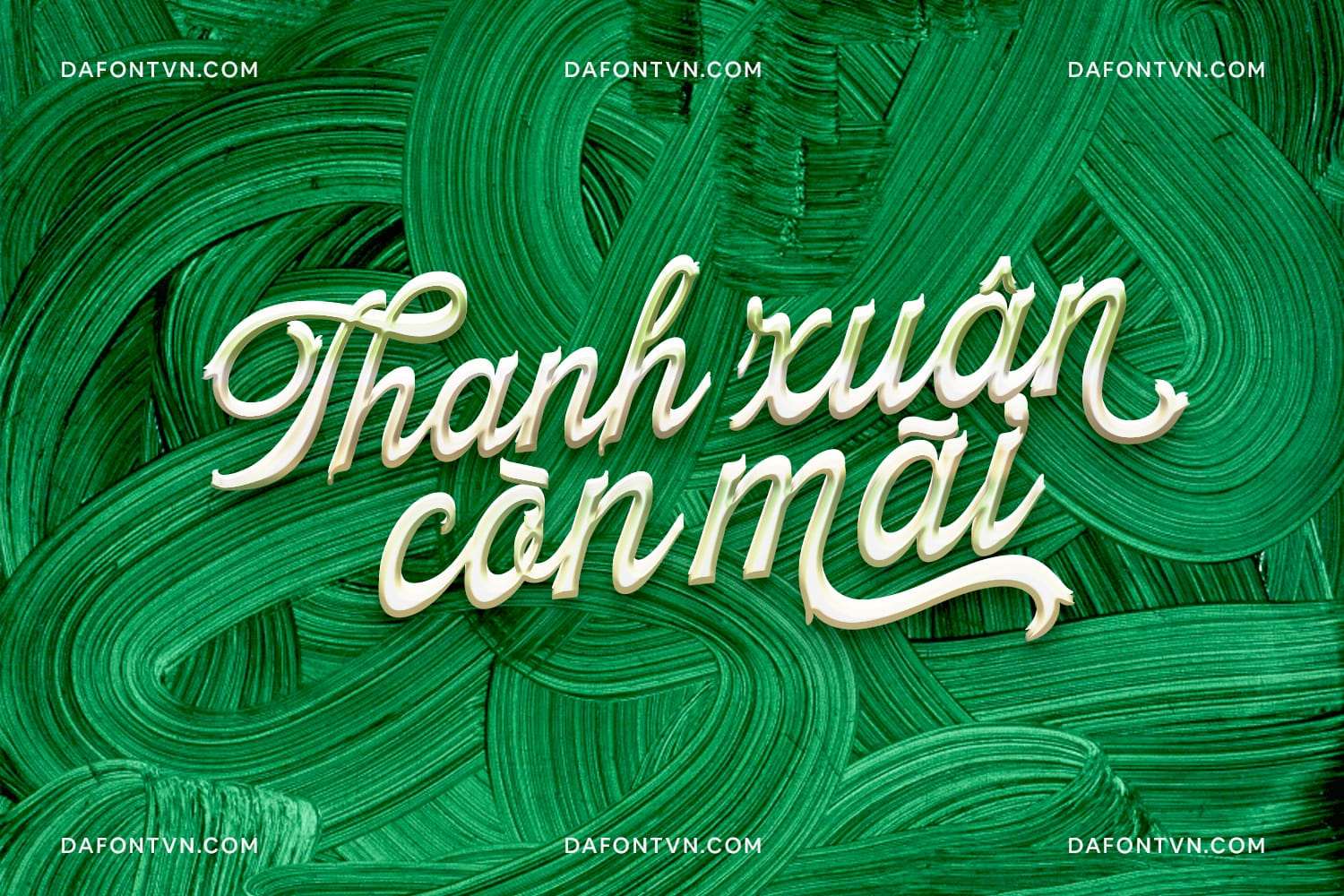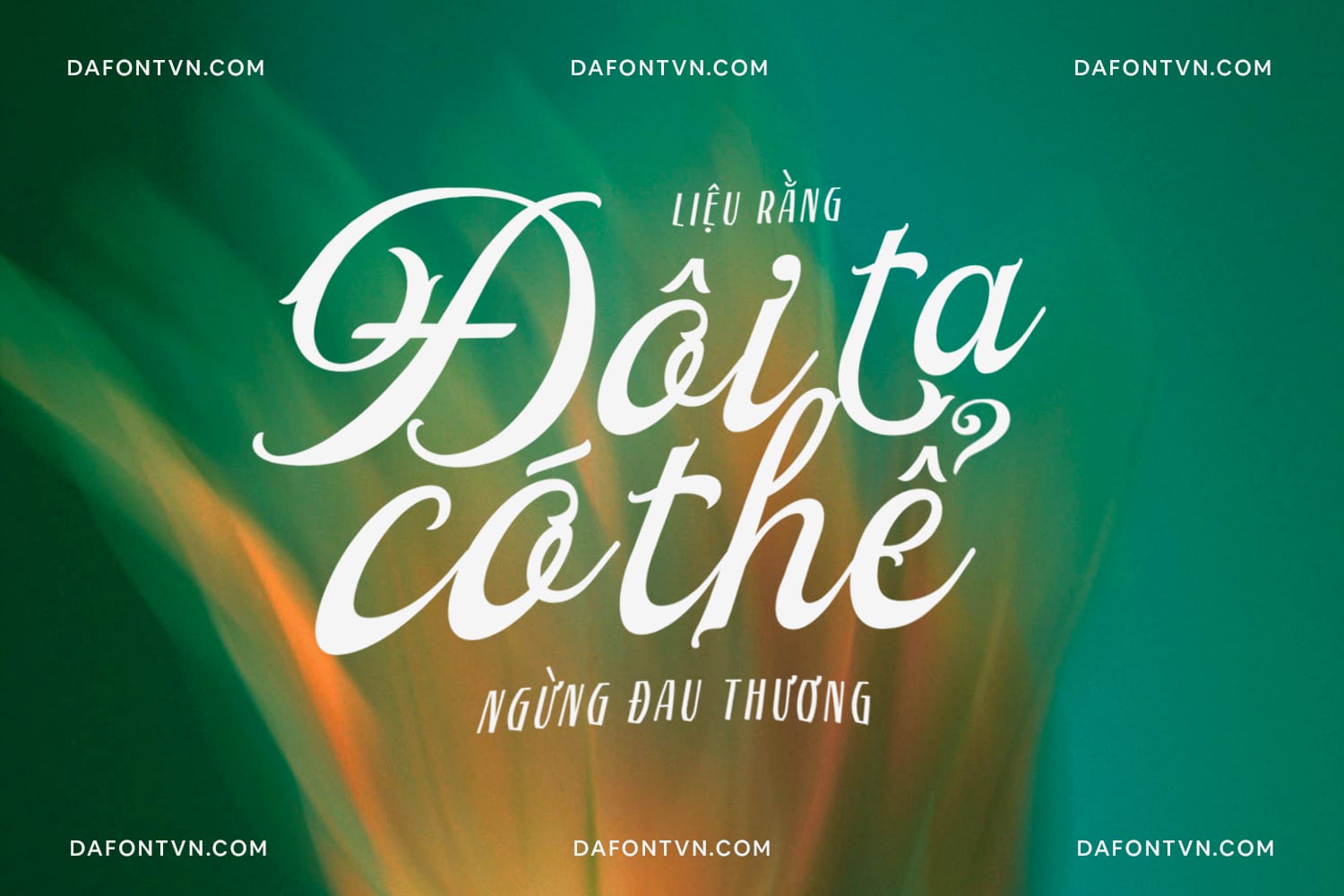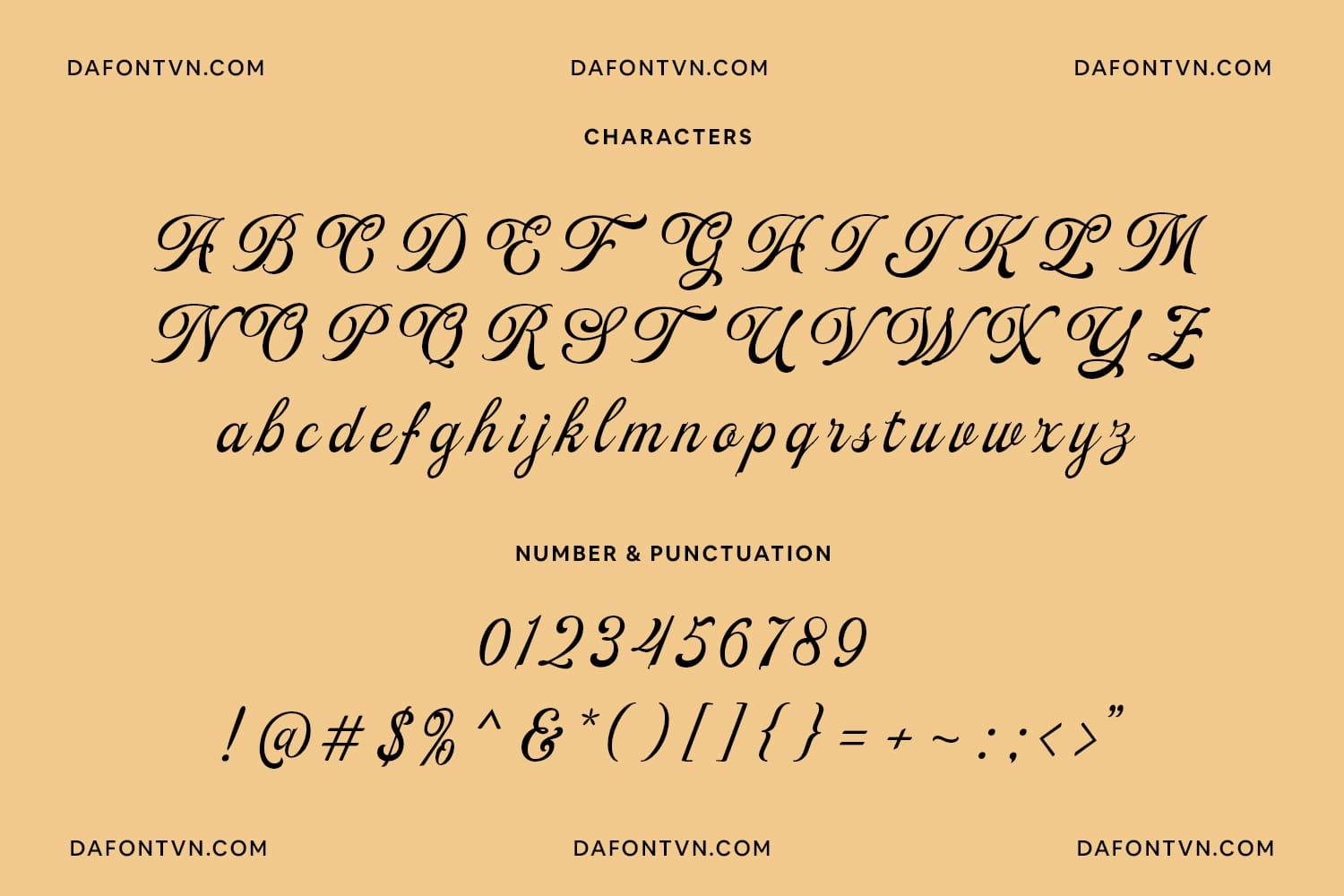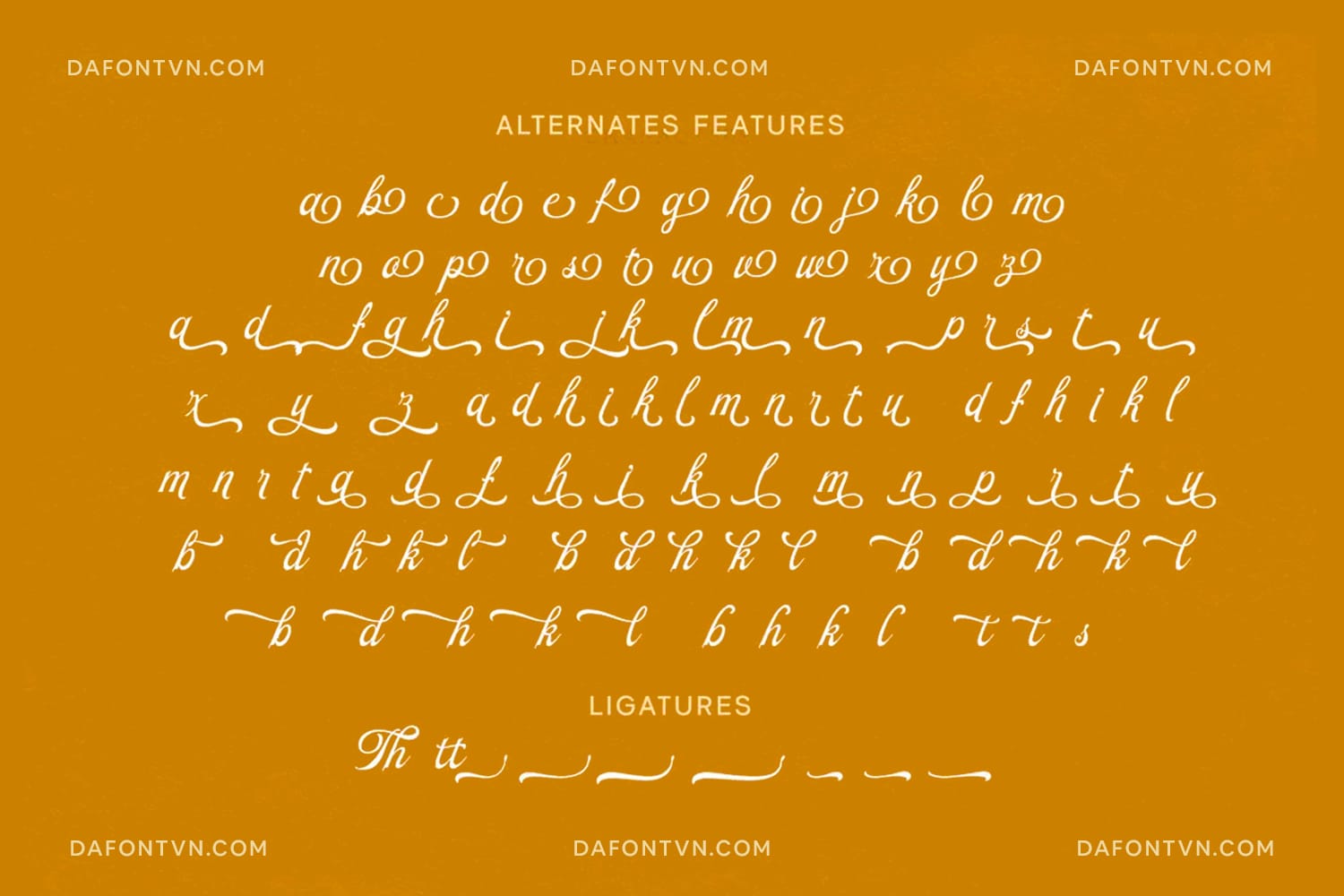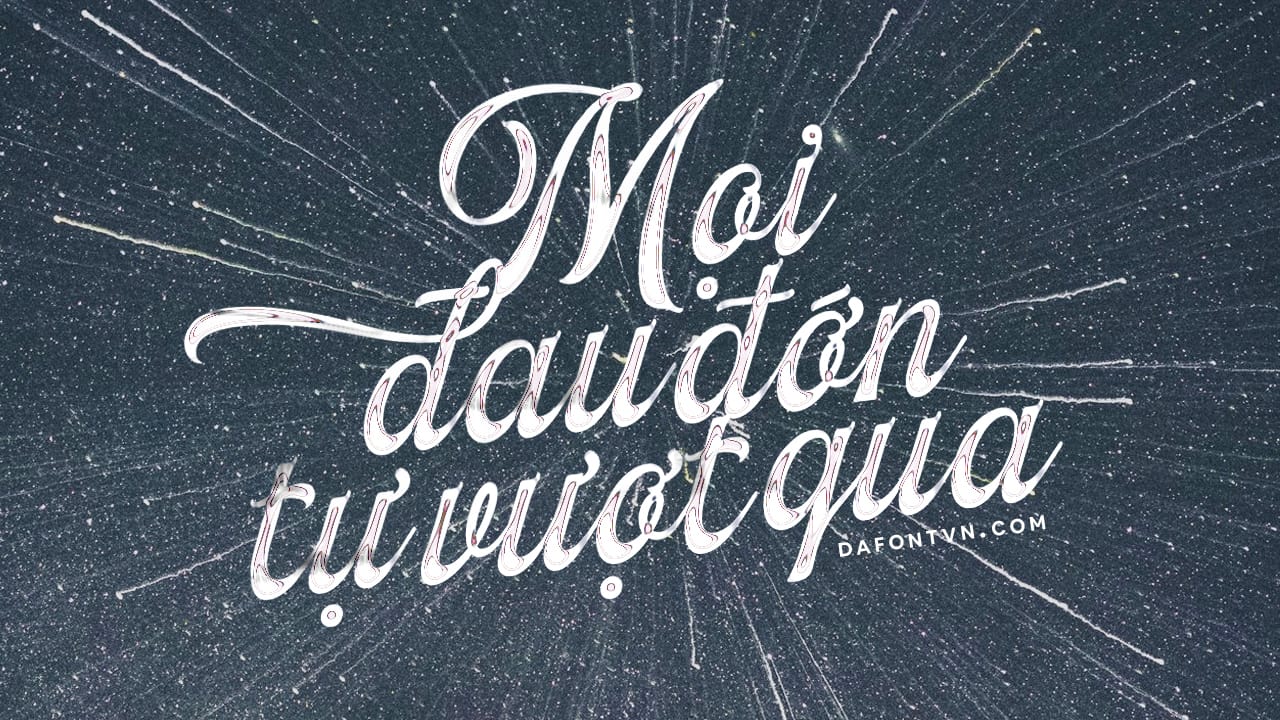
Beauty Reflections Font là một font script trang nhã thể hiện tính nghệ thuật của thư pháp với một chút duyên dáng và hiện đại. Các dạng chữ được chế tạo cẩn thận tạo nên sự khởi sắc tinh tế và các chi tiết phức tạp, thể hiện sự cân bằng hoàn hảo giữa sự sang trọng và đi kèm với phiên bản thông thường và phiên bản tùy chỉnh.Phông chữ Beauty Reflections được thiết kế hoàn hảo để áp dụng cho nhiều thiết kế khác nhau đặc biệt là trong logo và các hình thức trang trọng khác nhau như thiệp mời, nhãn hiệu, logo, tạp chí, sách, thiệp chúc mừng / đám cưới, bao bì, thời trang, đồ trang điểm, văn phòng phẩm, tiểu thuyết, nhãn hiệu hoặc bất kỳ loại nào.